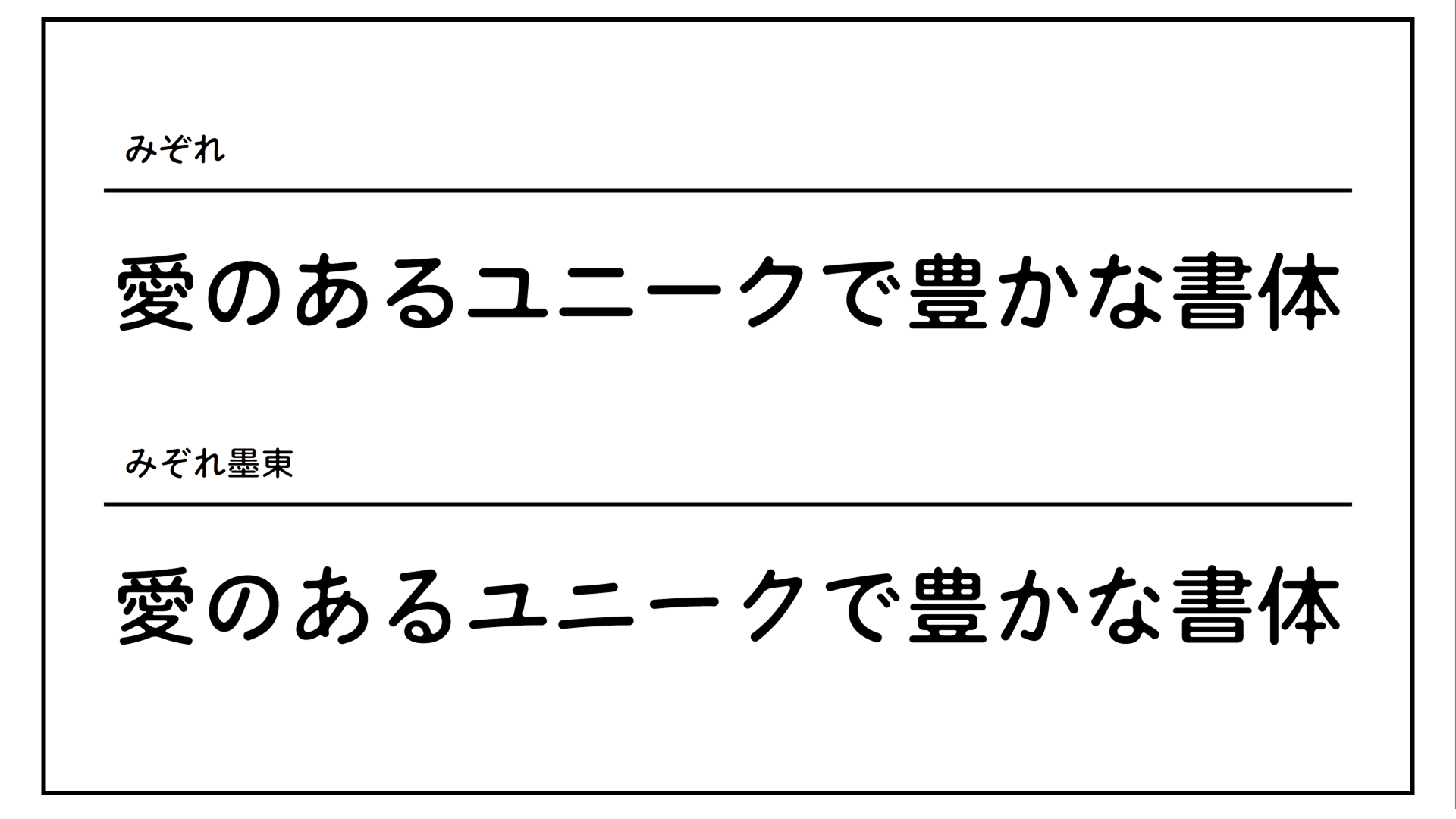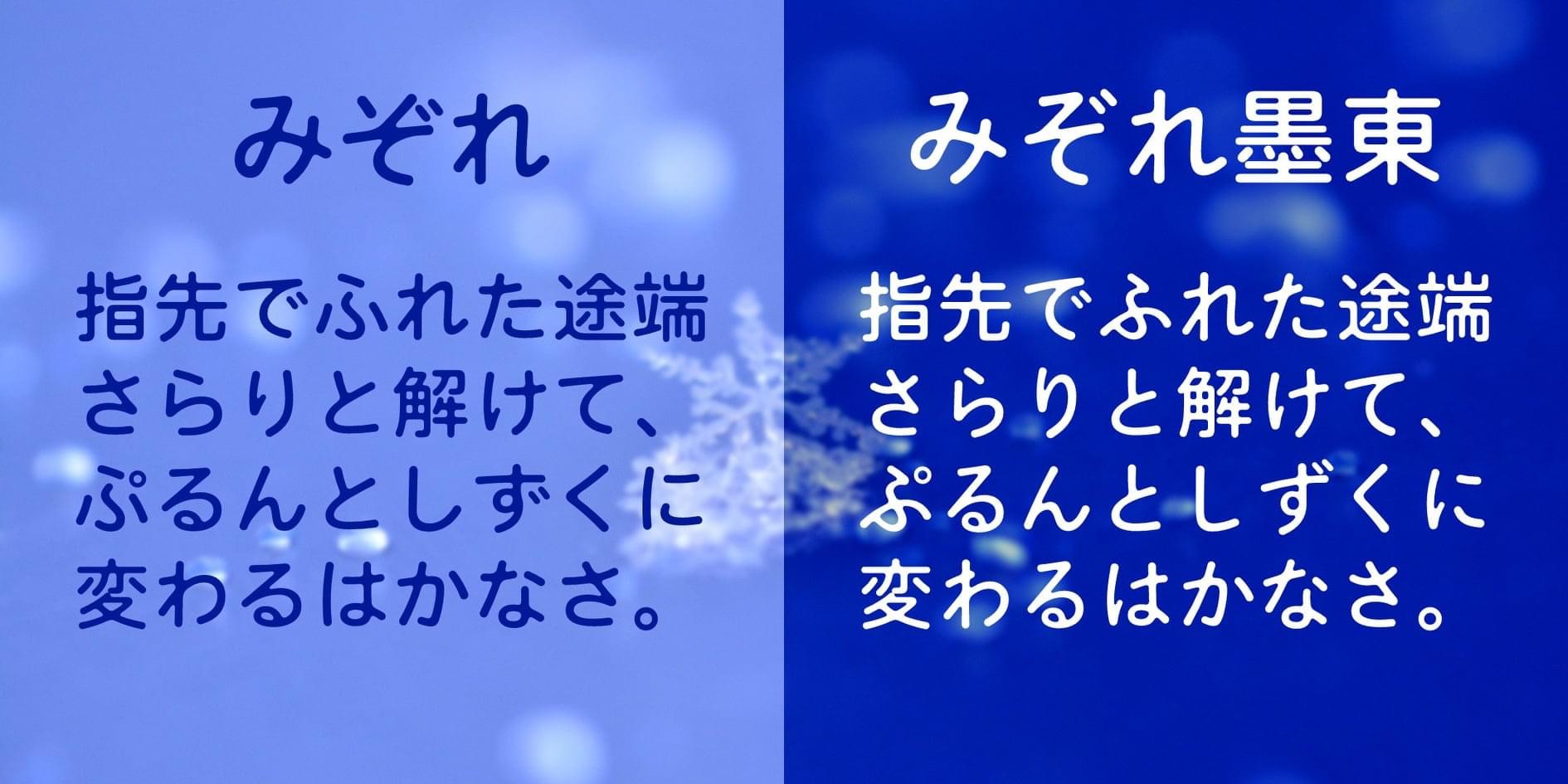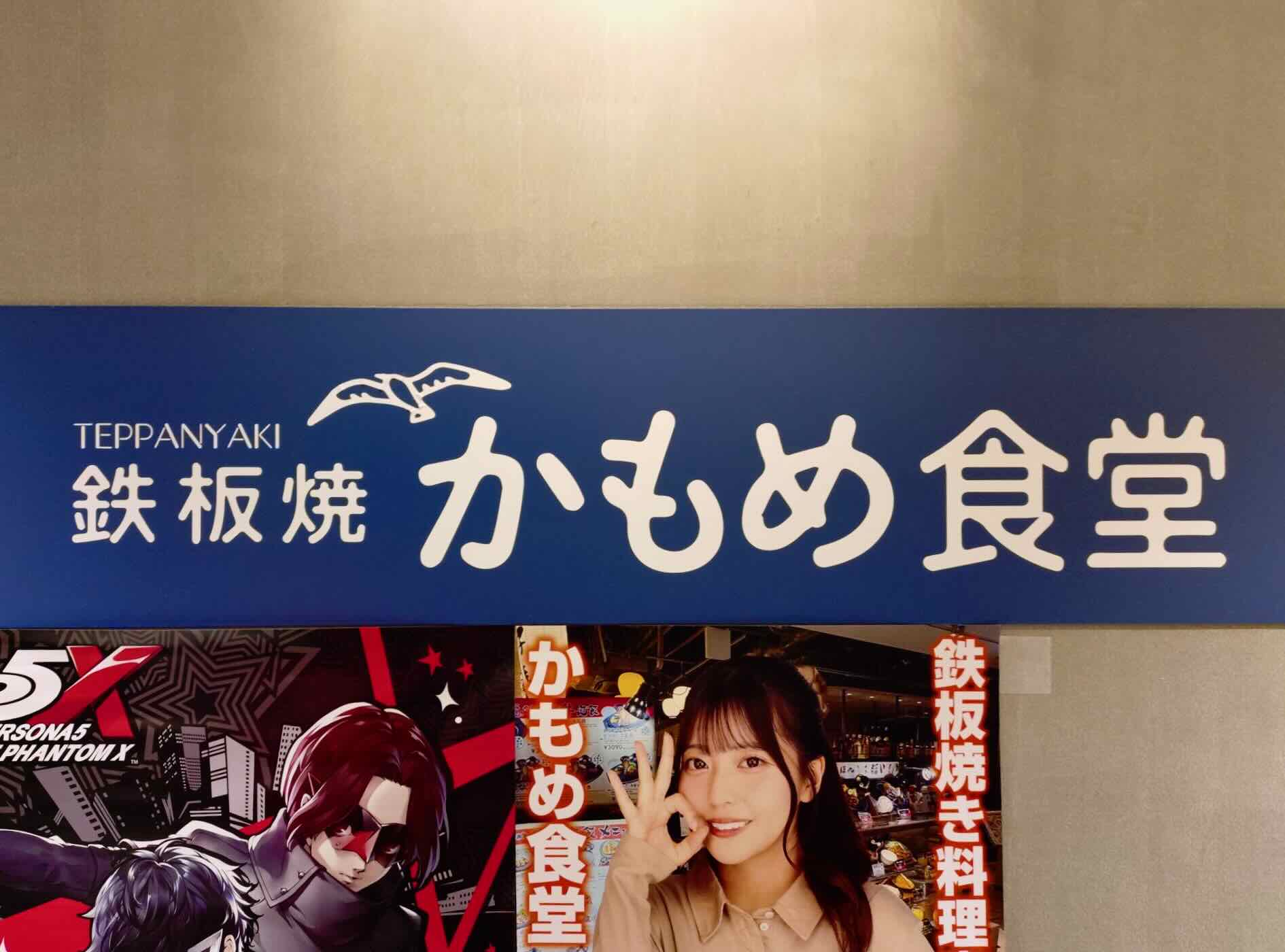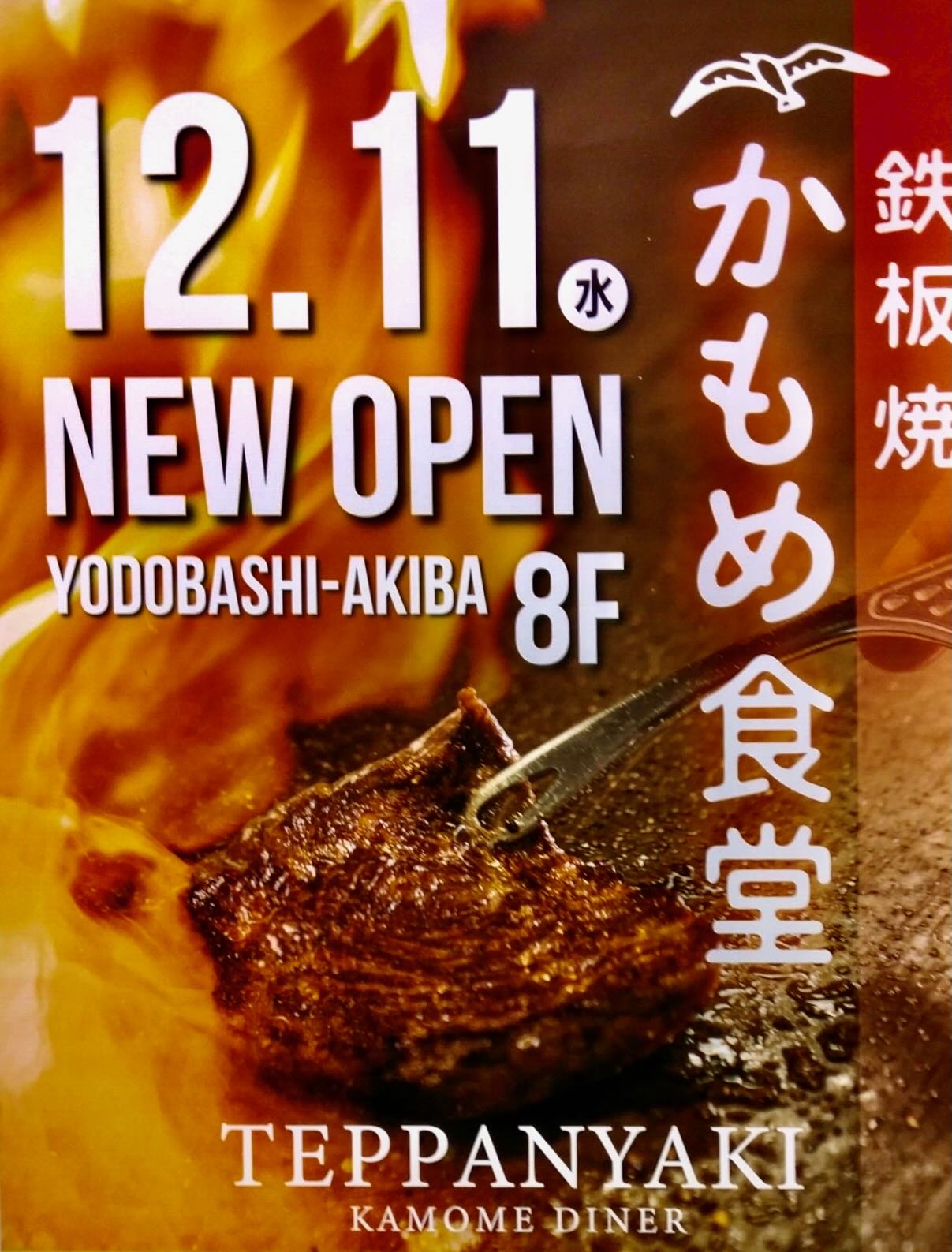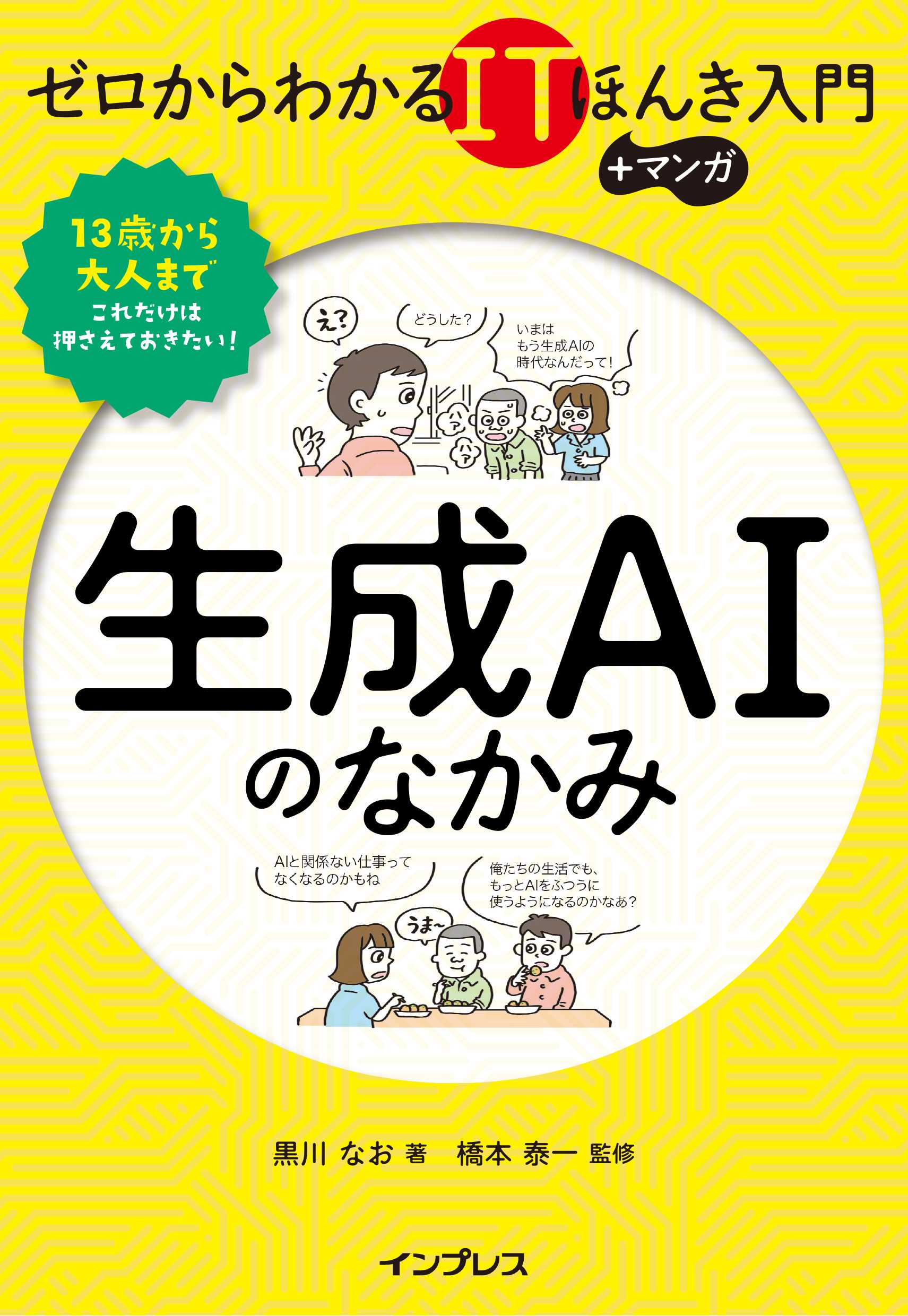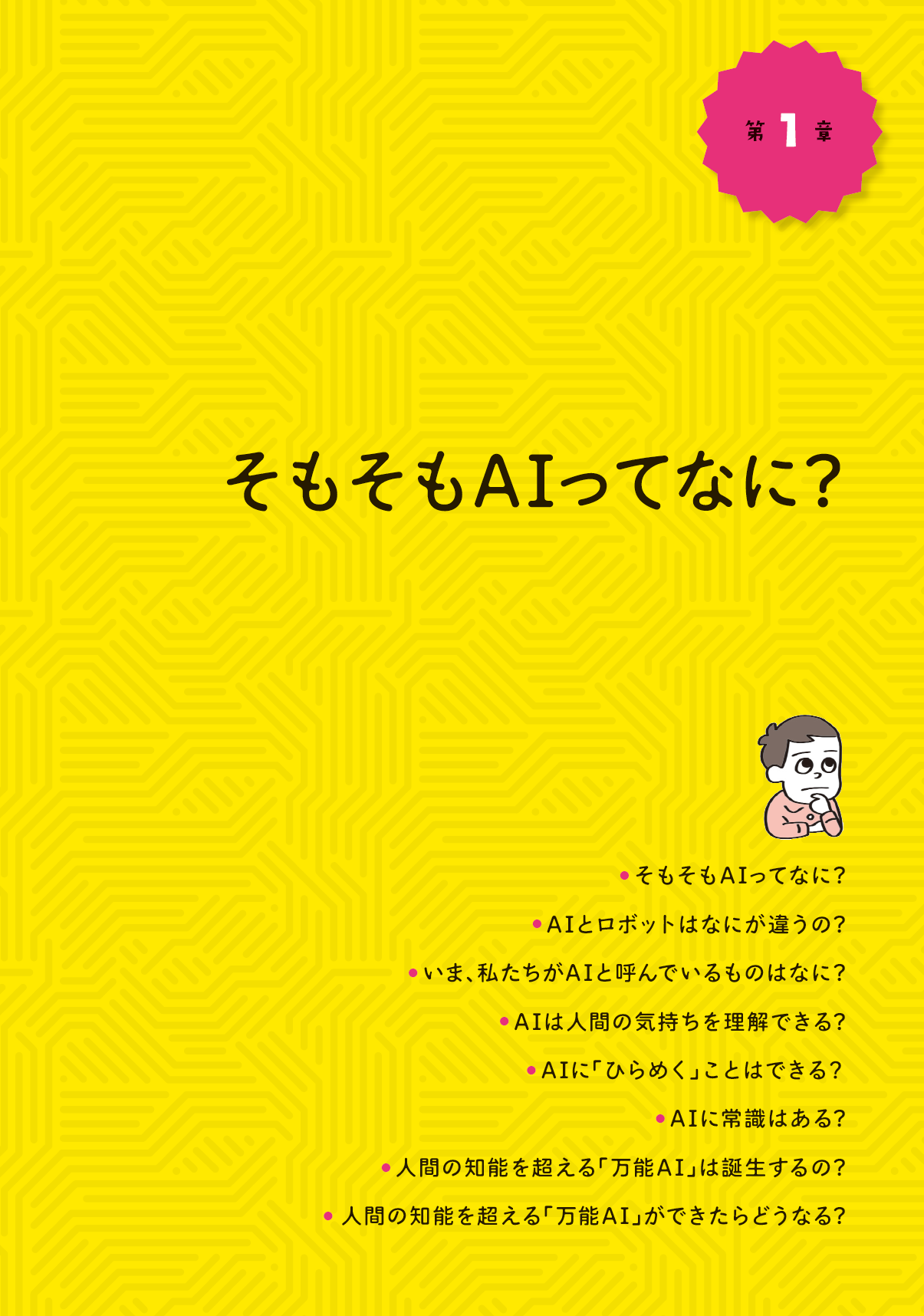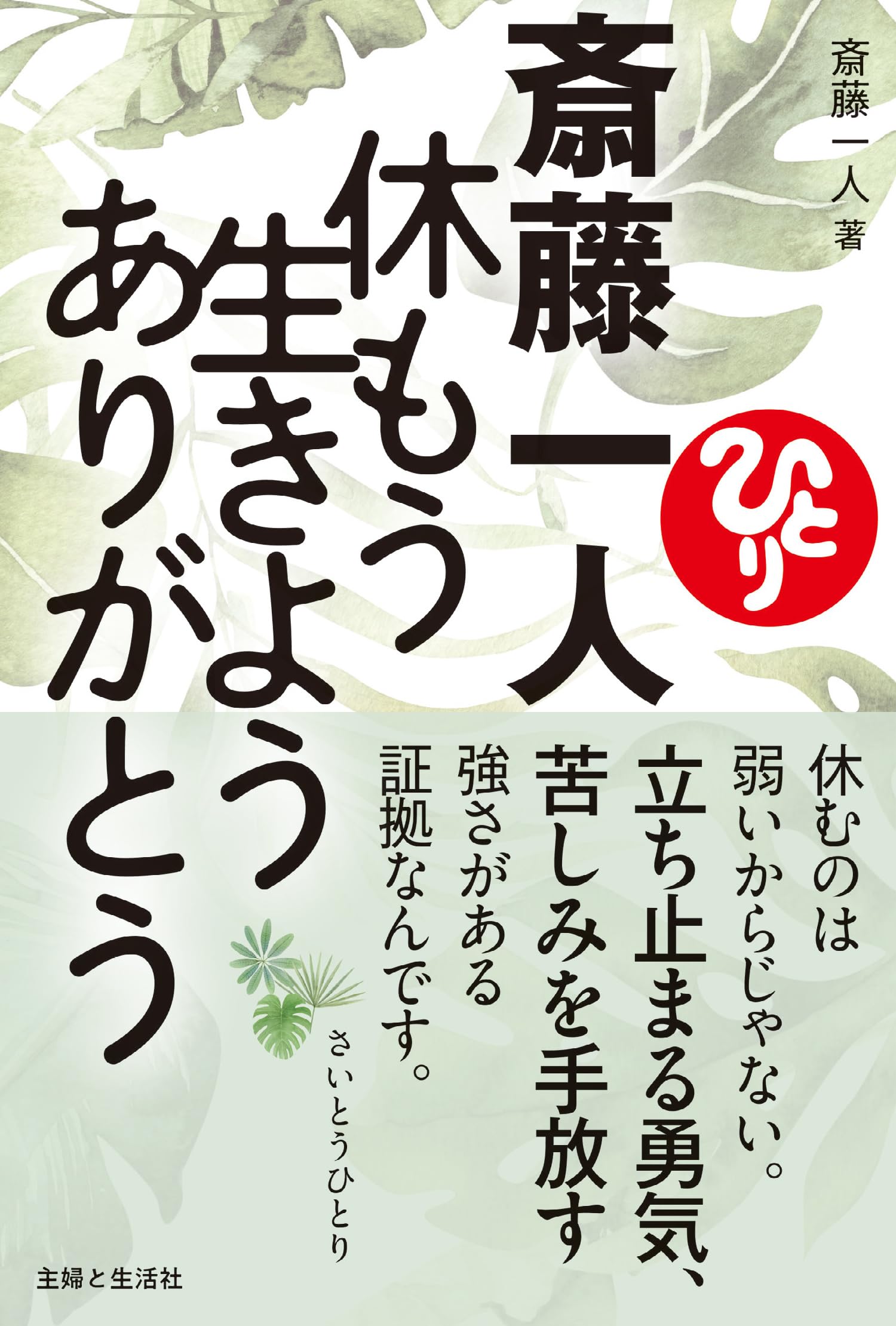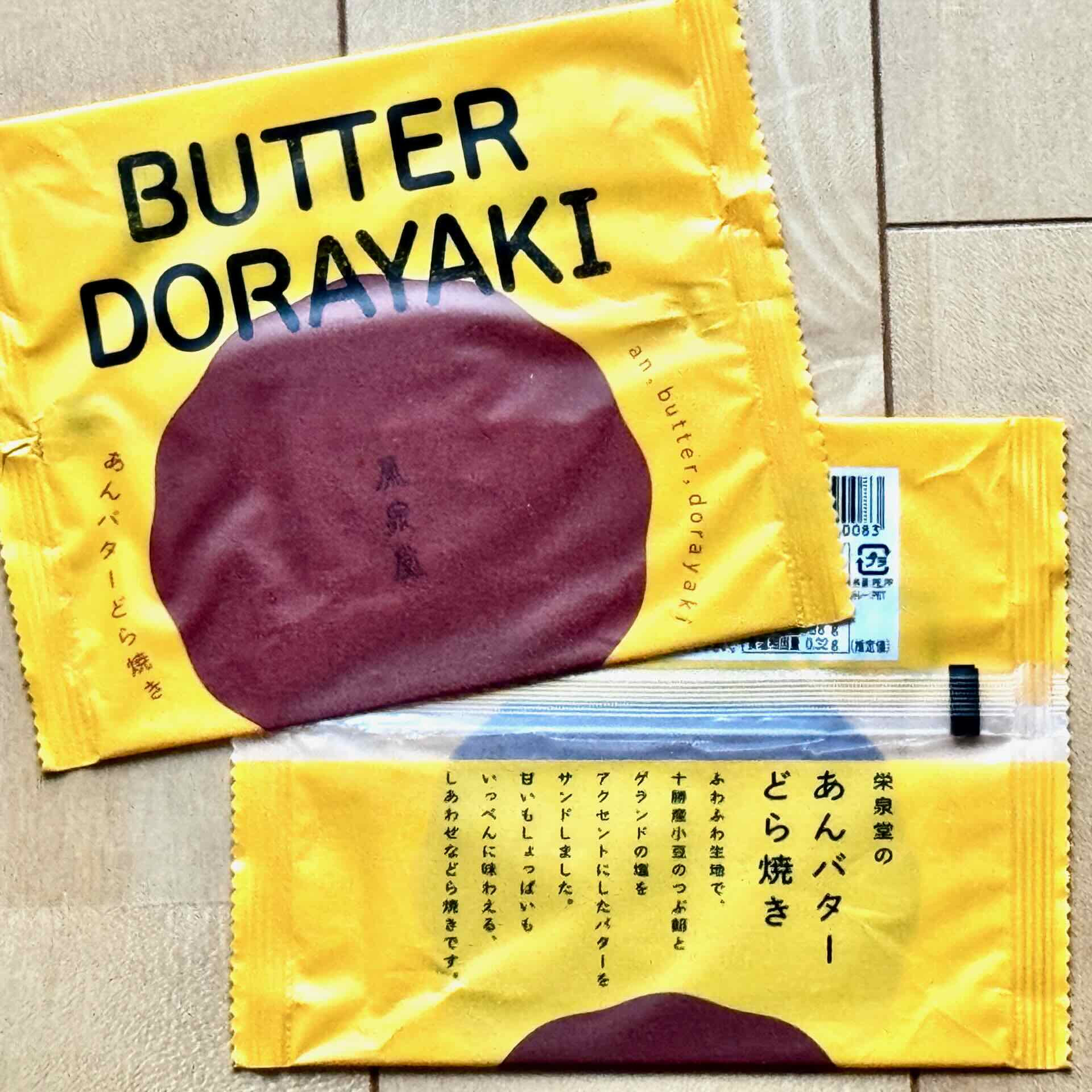
丸ゴシック書体の線画の交点をキレイに丸くしたフォント
菓子の袋 さとうゆたか
仙台栄泉堂の「あんバターどら焼き」。
BUTTER DORAYAKIの文字に、みぞれ墨東の英字フォントが使われている。
すこし加工されているが、自分が作ったフォントは、すぐに分かるんだな…。
あ さとうゆたか
英字部分だけ。
10個入りの箱に付いていた、のし紙。
あ さとうゆたか
個別袋の裏の説明文は、しっかりと「みぞれ墨東」。
本の表紙 さとうゆたか
みぞれ墨東の使用例。
書名:休もう生きようありがとう
著者:斎藤一人
発行:主婦と生活社
あ さとうゆたか
こちらは、新聞広告。
本の表紙 さとうゆたか
みぞれ墨東の使用例。
書名:生成AIのなかみ
著者:黒川 なお、橋本 泰一(監修)
発行:インプレス
同じシリーズ。
書名:Web3のなかみ
著者:黒川 なお、橋本 泰一(監修)
発行:インプレス
まだあった…。
「生成AIのなかみ」の扉ページ。
店名ロゴ さとうゆたか
みぞれ墨東の使用例。
秋葉原のヨドバシ内にある店らしい。
もうひとつ。
この店がオープンした時はまだ、この太さのフォントは頒布していなかったから、標準の「みぞれ墨東」を加工したのだろう
そのせいか、すこし輪郭線が崩れているようだ。
みぞれ 太字フォントの頒布開始! さとうゆたか
本日、頒布開始しました。
横組みサンプルです。
みぞれ墨東 太字フォントの頒布開始! さとうゆたか
本日、頒布開始しました。
横組みサンプルです。
幟旗 さとうゆたか
近所のファミレス(COCOS)の幟旗。
「ふわふわ かき氷」の文字が、みぞれ墨東。
広告画像 さとうゆたか
「みぞれ墨東」が見出しに使われている。
LOVOT(らぼっと)は、GROOVE X社が開発した次世代のコミュニケーションロボットのこと。
まだある。
もうひとつ。
書店で見かけた本の表紙 takumi
書名:何歳からでも遅くない 最高の生き方を手に入れる 人生再起動メソッド
著者:いれぶん
発行:イースト・プレス
「何歳」と「遅くない」が、みぞれ墨東ですね。